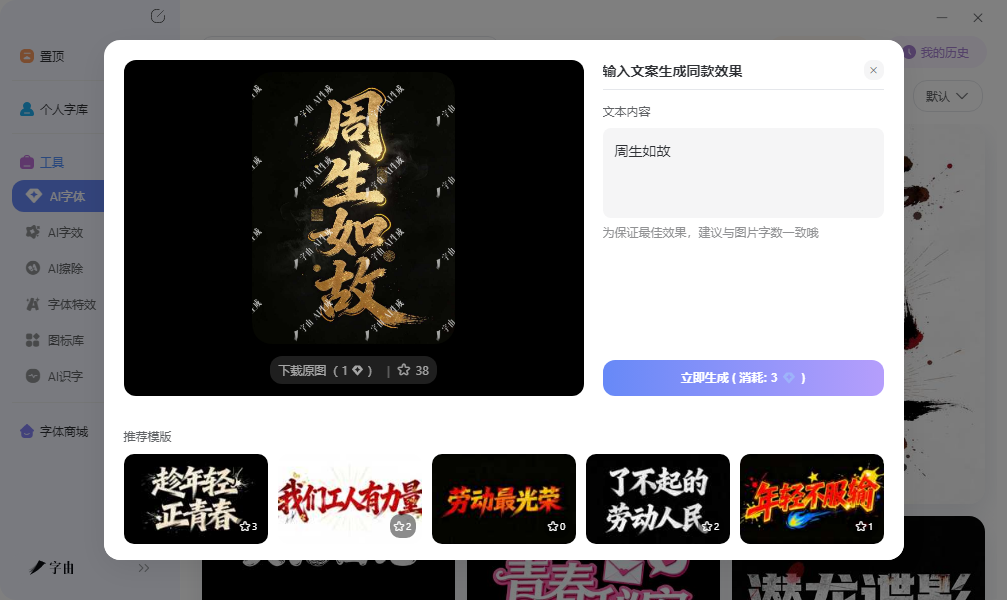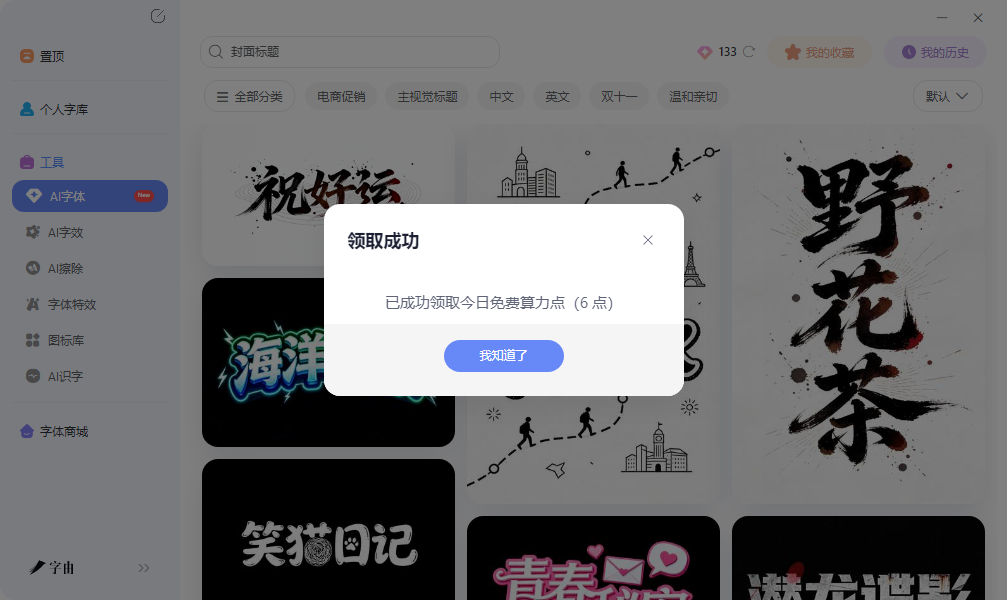
书法字体生成不用愁,从字由AI到书法模板一篇看懂
做国潮海报缺个有冲击力的标题,或者给茶叶包装找一款有文化感的书法字,以前只能请书法老师写,或者从网上下载字体。现在有了字由以后一切都变得方便很多,:一是AI字体功能,输入文案选个书法模板,几十秒拿到一张特效字图,国潮、水墨、鎏金都有;二是字体库本身,颜真卿楷书风格的“字由颜楷”、“演示悠然小楷”这种现成的书法字体,点一下激活就能在PS里用。下面就会详细介绍字由的这两个功能,让你找到心仪的书法字体。
1、字由AI字体:直接选模板即可
如果你需要一张现成的书法字图,直接放海报或封面上用,不需要反复修改文字内容,字由的AI字体是最快的路。
打开字由客户端,在顶部导航栏找到“字体工具”下的“AI工具”,再点“AI字体”,你会看到一个分类好的模板库。想找书法类模板,直接在搜索框里输入“国潮”“书法”“中国风”,或者在左侧筛选栏里找到“国潮风”分类,所有书法相关的模板一次性列出来。
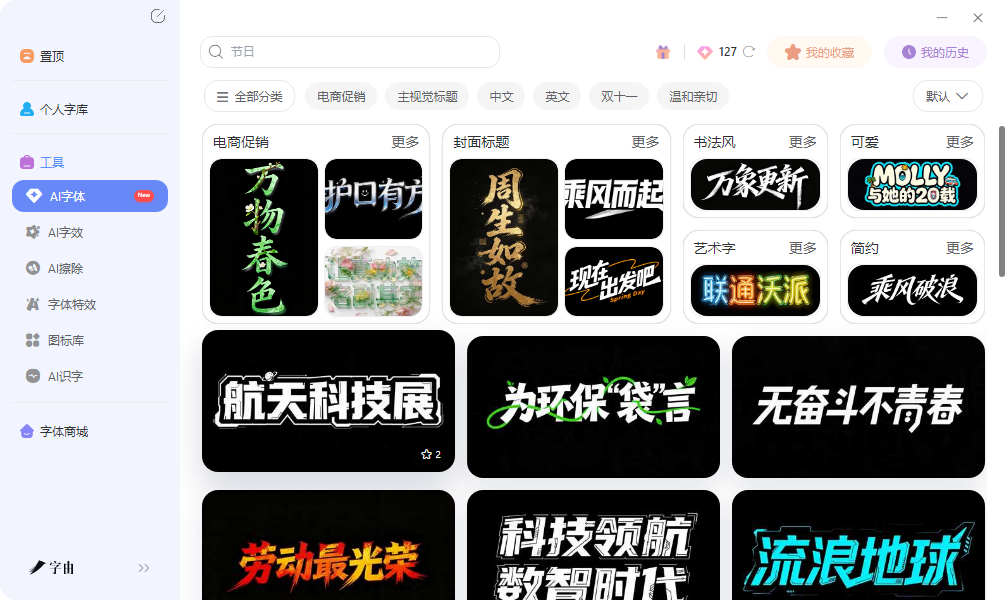
国潮风的模板种类非常丰富。鎏金书法字效果,金色渐变配上仿古纹理,适合做中式品牌Logo、高端礼盒包装;水墨晕染字效果,边缘像墨迹自然渗开,适合做茶品牌海报、山水旅游宣传;印章式文字效果,文字排成方章或随形章,适合做画册封面、文创贴纸;祥云纹样字效果,笔画出带云纹装饰,适合做节日贺卡、非遗项目视觉;碑刻拓印效果,斑驳的拓印质感,适合做历史纪录片标题、古籍复刻设计。每个模板都有预览图,鼠标滑过就能看到用你的文字实时展示的效果,不用点进去就能大致判断适不适合。
选定模板后,点击“做同款”,在右侧输入框里把模板里的文字换成你自己的文案。有一个小细节:最好和模板原本的字数保持一致。比如模板是四个字就填四个字,是两个字就填两个字,否则排版容易走形。确认后点“立即生成”,等待25到30秒,系统就会输出一张高清艺术字图片。如果是制作国潮风格,生成效果与模板示例风格吻合,笔画也保留了手写感,没有常见的错字或变形问题。
2、书法风字体激活
AI字体生成图片适合“一次性使用”,每张图都是独立的。但如果你需要一款书法字体能反复打出不同的字,用在不同页面里,那就要走字体库激活这条路。
字由的字体库里收录了大量现成的书法字体,按风格分的很细:楷书(方正端严,适合正式场合)、行书(流畅连笔,适合文艺风格)、草书(奔放狂野,适合强视觉冲击)、隶书(古朴扁宽,适合牌匾招牌)、篆书(圆转流畅,适合印章设计)。打开字由客户端,在左侧筛选栏里找到“字体类型”>“书法体”,所有书法风格的字体一次性列出来。字由平台还收录了原创、书法、黑体、手写等多种特色字体资源。
重点推荐几款字由里的书法字体:
- 字由颜楷:以唐代颜真卿早期楷书典范《多宝塔碑》为蓝本,通过数字化技术精研重构。字体取碑刻原作的方正端严之态,保留颜体特有的筋骨丰盈、笔力遒劲特质:横细竖粗对比鲜明,起笔方峻而收笔浑厚;点画顿挫如金石铿锵,转折处提按分明,凸显唐代楷书法度森严的气象。适合书籍封面、文化宣传册、非遗项目、高端文旅品牌、历史剧字幕。
- 演示悠然小楷:出自一位99年出生的书法专业在读学生之手,字迹在娟秀中也沉积着力量,宛如初来乍到、稍带拙气的小师妹。用在PPT上既有手写体的张力又不至于夸张轻浮.
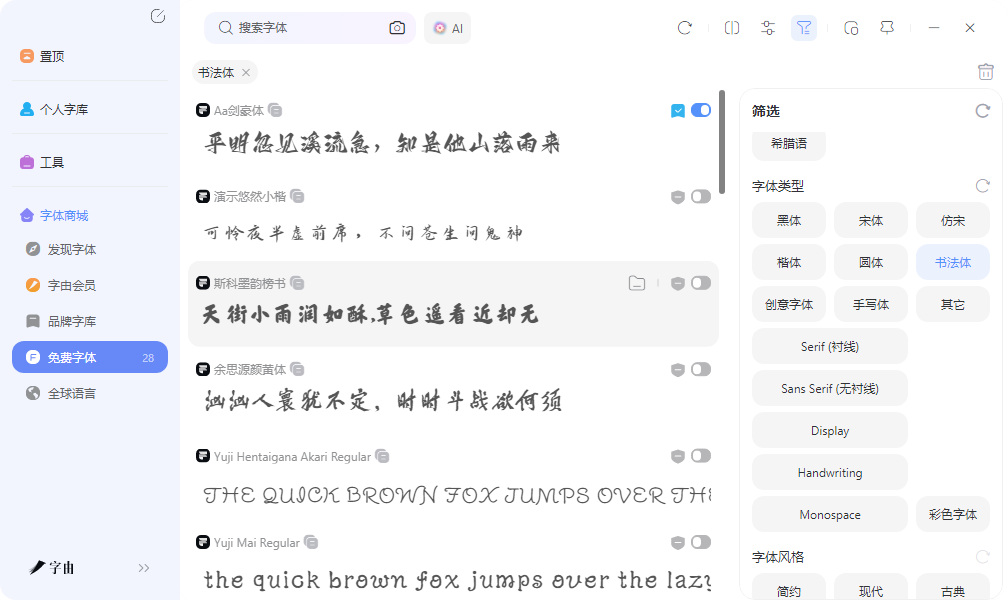
- 字由还和汉仪字库等专业厂商合作,平台上书法字体资源丰富,汉仪的合作字体在包装、品牌领域口碑很好。此外,字由还推出了优设系列字体,专门针对设计领域免费字体数量少且一致性欠佳的问题开发,在专业性方面较为突出,字型尽显美丽。